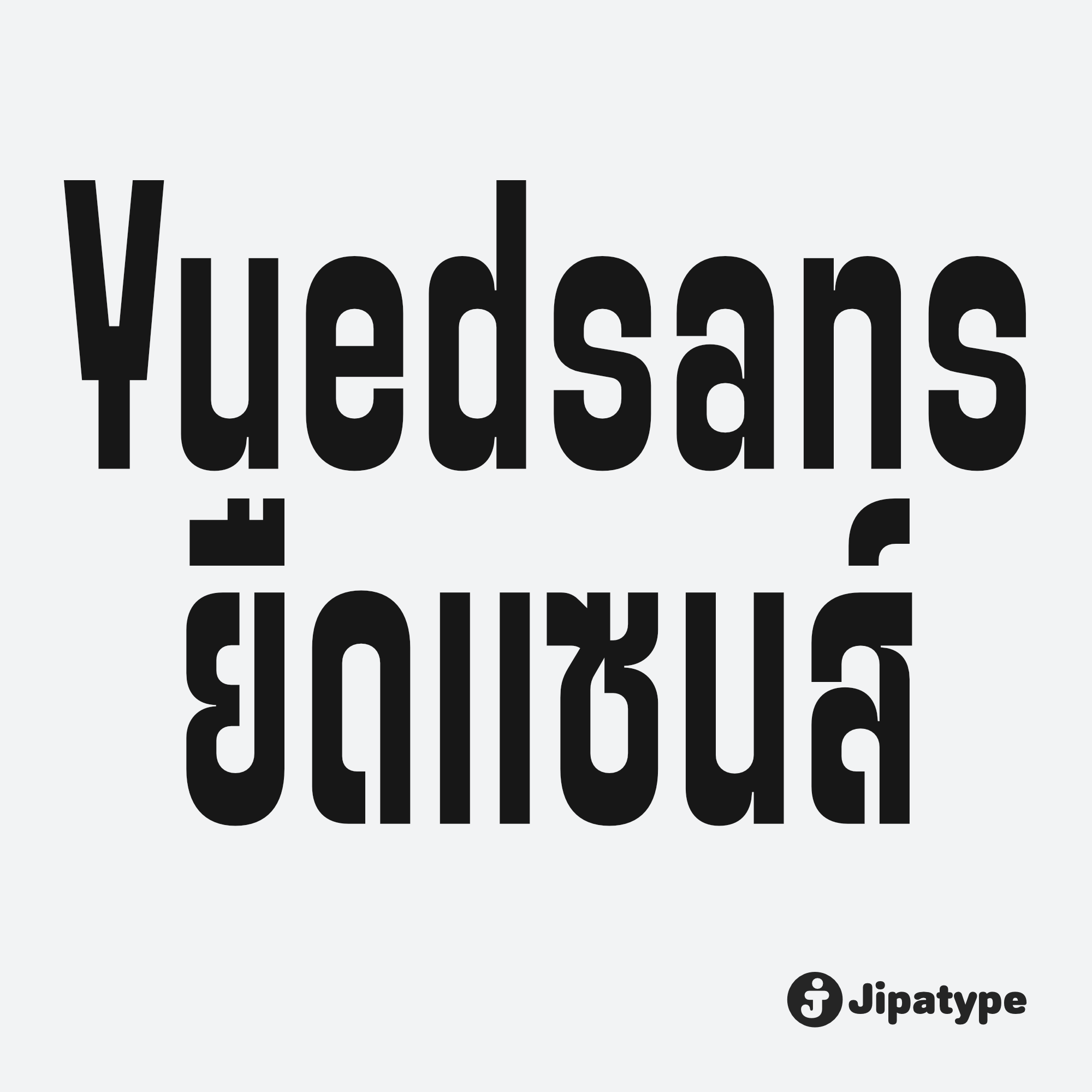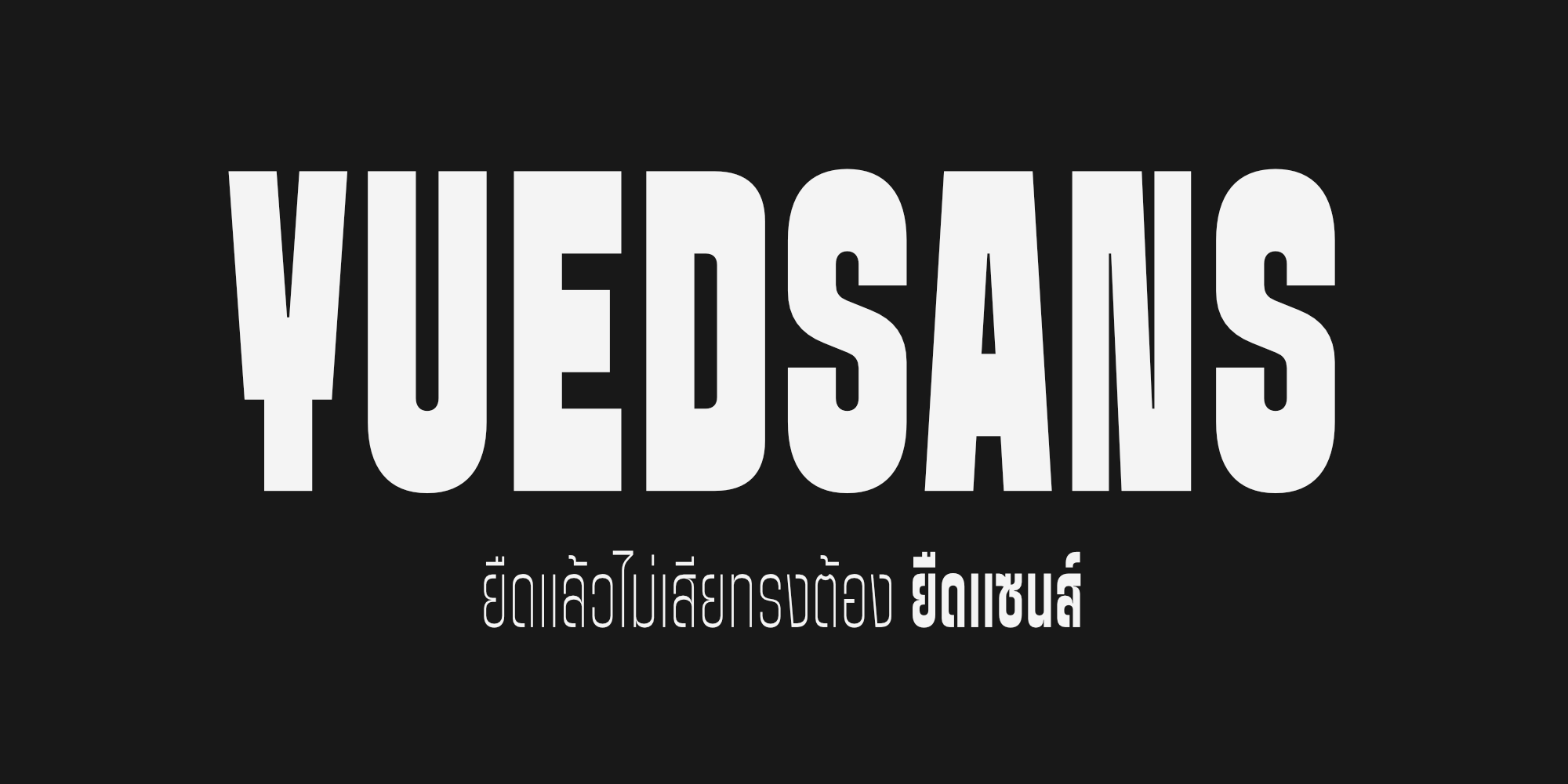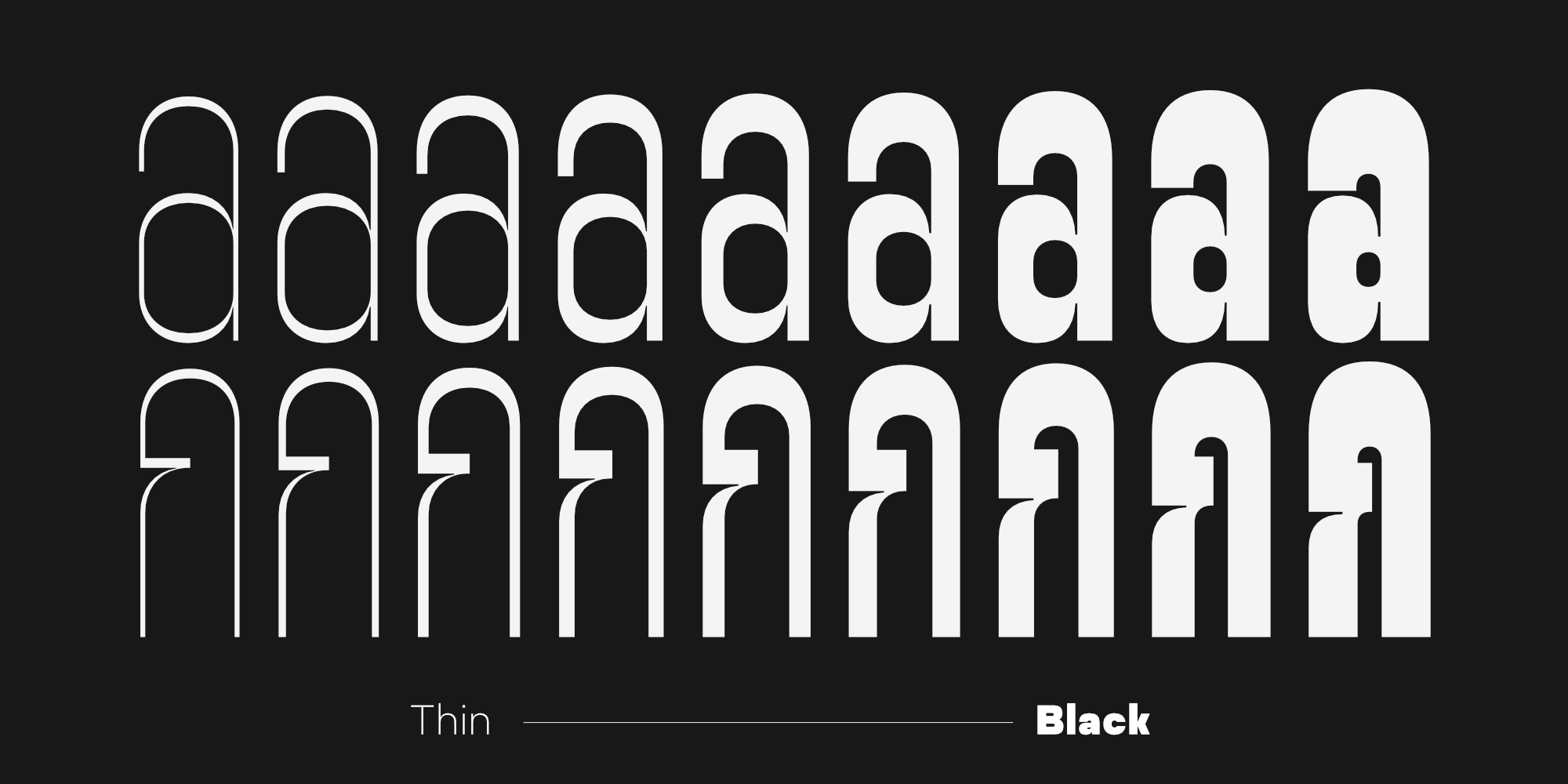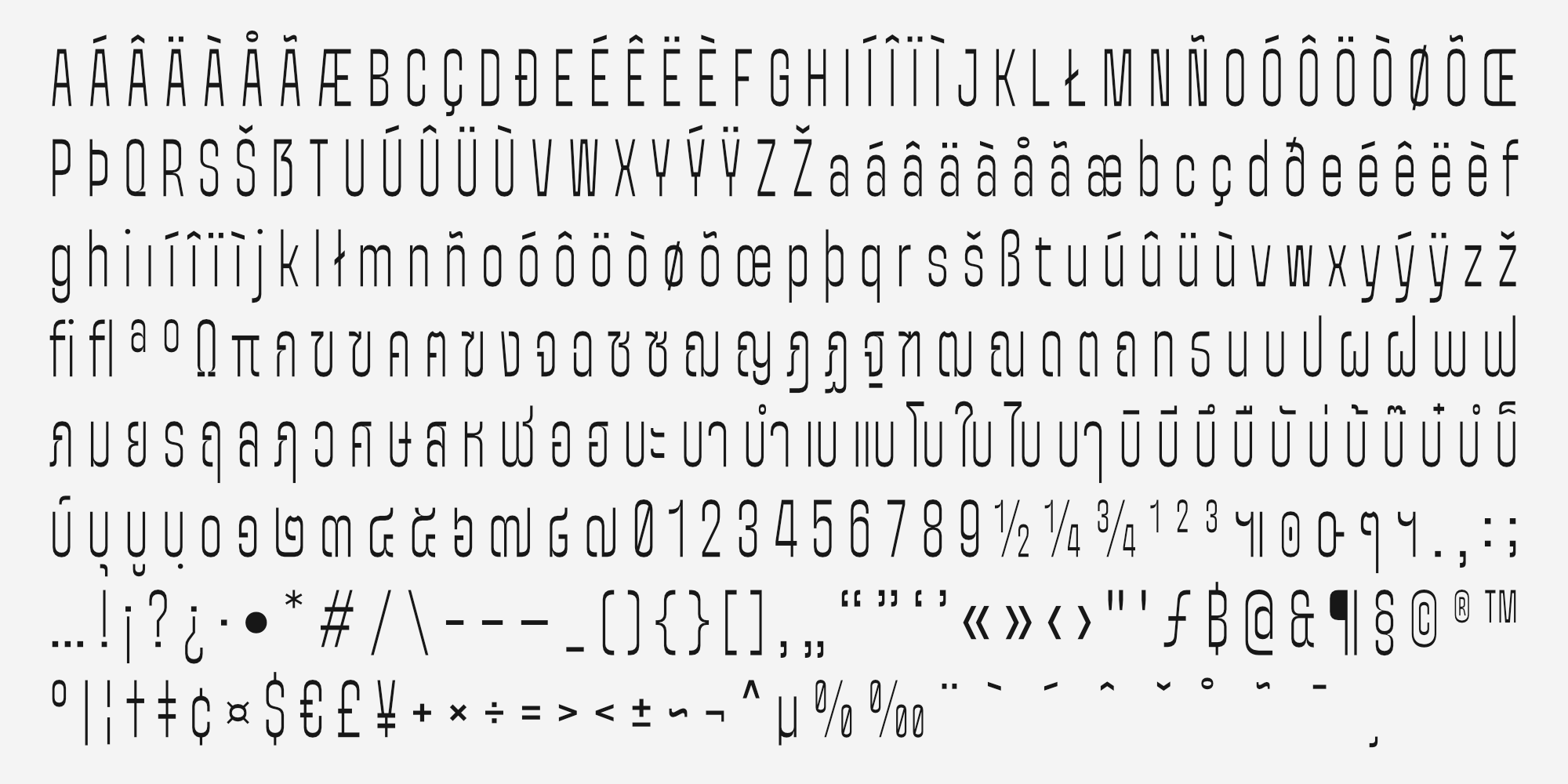
Yuedsans เป็นชุดแบบอักษร Sans-serif สไตล์ Condensed ที่โดดเด่นด้วยสัดส่วนที่แคบและสูงชะลูด ให้ภาพลักษณ์ที่ดูทันสมัย โฉบเฉี่ยว และมีความมั่นใจ
การออกแบบได้รับแรงบันดาลใจจากสุนทรียะของการ “ยืด” ตัวอักษรในงานกราฟิกยุคใหม่ แต่ผ่านการปรับปรุงโครงสร้างเส้น ให้มีความสม่ำเสมอและสมดุลทางทัศนศิลป์ ทำให้ตัวอักษรไม่ดูบิดเบี้ยวเหมือนการถูกบีบอัดด้วยซอฟต์แวร์ แต่กลับดูแข็งแรงและเป็นระเบียบ
ด้วยโครงสร้างที่ประหยัดพื้นที่ในแนวนอน Yuedsans จึงเป็นตัวเลือกที่ยอดเยี่ยมสำหรับการใช้งานในพื้นที่จำกัดแต่ต้องการความโดดเด่นสูงสุด เหมาะอย่างยิ่งสำหรับงานออกแบบพาดหัว, ป้ายโฆษณา, โปสเตอร์, งานออกแบบบรรจุภัณฑ์, สื่อแฟชั่นแนวสตรีท, และโลโก้แบรนด์ที่ต้องการสื่อสารถึงความทันสมัยและความกระฉับกระเฉง
นอกจากนี้ยังรองรับน้ำหนักที่หลากหลาย ตั้งแต่ตัวบางสุดไปจนถึงตัวหนาเข้ม ทำให้สามารถเลือกใช้เพื่อสร้างลำดับความสำคัญของเนื้อหาในงานออกแบบได้อย่างมีมิติ
ออกแบบโดย : อานุภาพ ใจชำนาญ (Anupap Jaichumnan)